20+ من أفضل الخطوط المجانية للمصممين ستجدها مفيدة
نشرت: 2016-03-16اصحاب! عدنا اليوم بمجموعة من أكثر من 20 من أفضل الخطوط المجانية للمصممين الذين ستجدهم مفيدة. هذه خطوط جميلة وحديثة وفريدة من نوعها ومجانية تمامًا للتنزيل والاستخدام. لذا ، تحقق منها وأضفها إلى مجموعة الخطوط الخاصة بك الآن. بالتأكيد ستجدها مفيدة في وقت ما في المستقبل.
1. الخط المجاني بخط اليد - Airpena
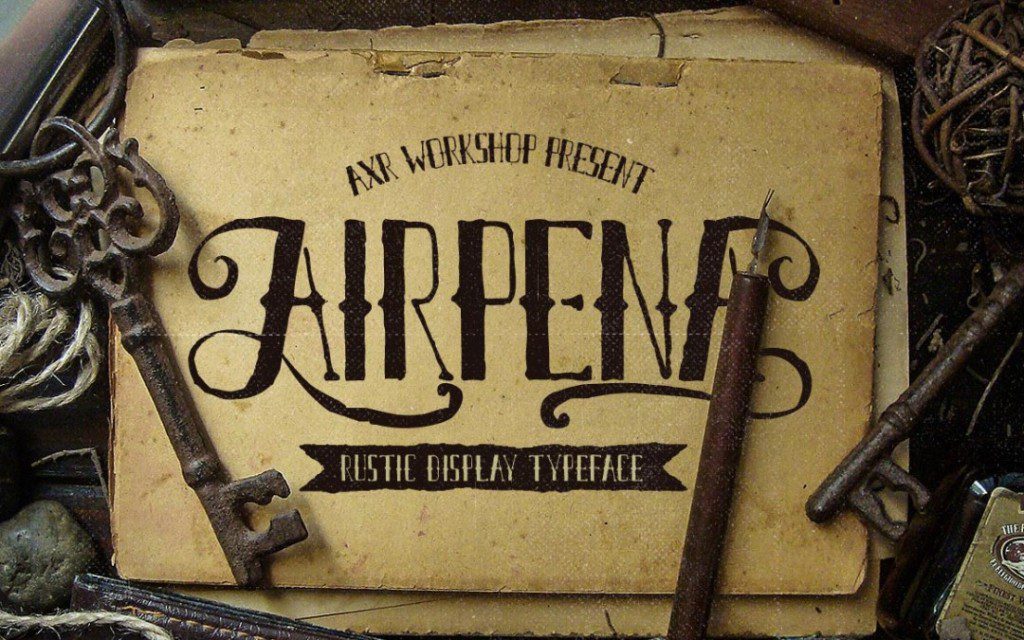
هذا محرف مجاني مستوحى من حروف مرسومة باليد صدئة ومؤلمة مستخدمة في دراجة نارية قديمة. يأتي مع بدائل أبجدية كاملة للأحرف الكبيرة (أمامي ونهاية) وأحرف صغيرة (نهاية).
2. Luxia - Modern Free Font
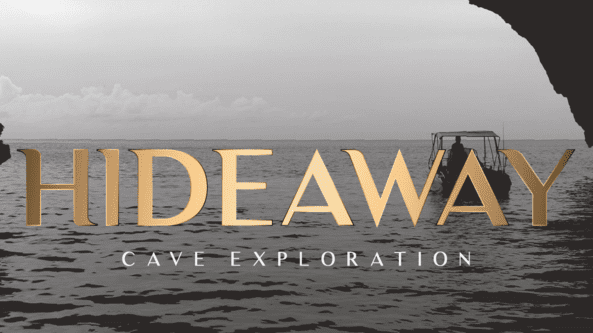
ألقِ نظرة على Luxia - ديدون حديث من سان سيريف مع مجموعة من الشخصيات الفخمة. يتضمن 3 أنماط: شبه غامق ، وشبه غامق مائل. لا تتردد! قم بتنزيل الخط المجاني وإنشاء عناوين جميلة باستخدام المحرف.
3. خروج - خط مجاني
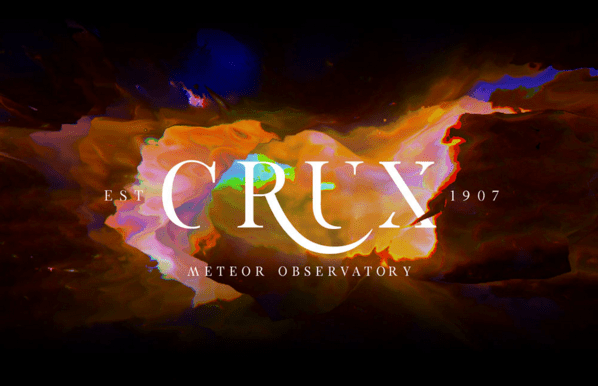
Exodus - خط مجاني بخطوط فاخرة. سيساعدك على إنشاء مجموعات أحرف فريدة من نوعها للشعارات والعناوين مع منح التحكم الكامل للمصمم. الهدية الترويجية من تصميم Andrew Herndon.
4. صوفيا - خط نصي للفرشاة Handlettered
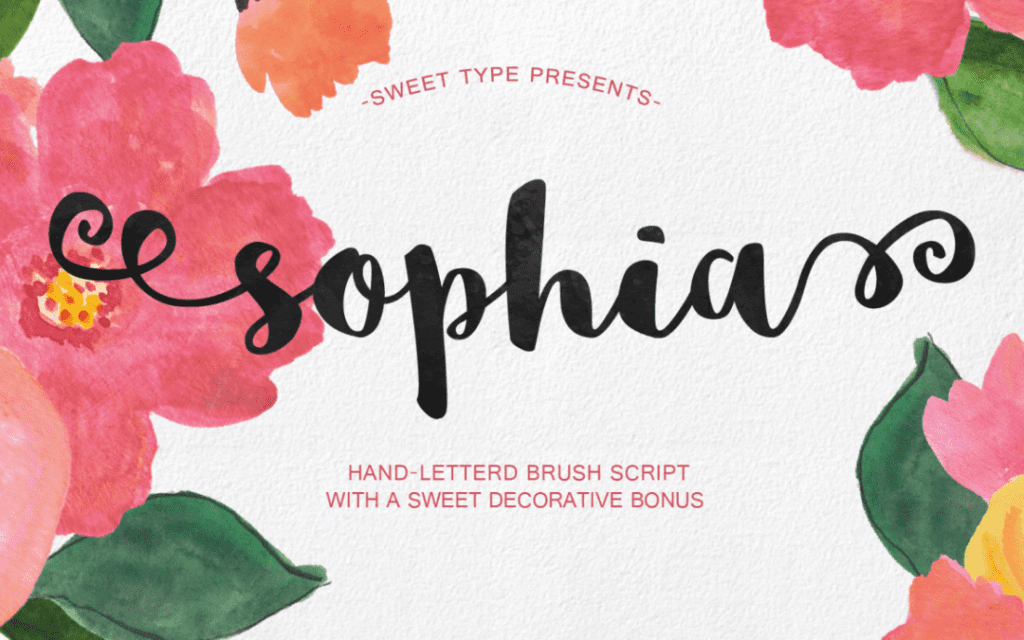
صوفيا - تنزيل جديد لخطوط فرشاة Handlettered Brush Script بواسطة إميلي سبادوني الموهوبة. في رأيي ، هذا الخط حلو للغاية ، بذيء وقليل من الرث. تسمح لك Sophia بإنشاء أنماط الكلمات المزخرفة الخاصة بك بسهولة. قم بالتنزيل مجانًا ببضع نقرات واستخدمها عبر مجموعة كبيرة من البرامج بما في ذلك Photoshop و InDesign و Illustrator و Microsoft Word بالإضافة إلى العديد من البرامج الأخرى.
5. Brusher الخط المجاني
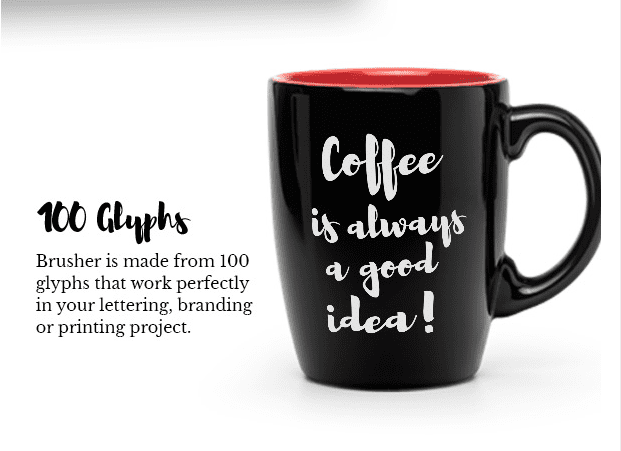
هذا خط تنزيل مجاني حديث وجريء للفرشاة يناسب تمامًا مشاريع التصميم المستقبلية الخاصة بك. يشتمل المورد على 100 صورة رمزية مصقولة بضربات دقيقة وخطوط ناعمة ستمنح النص مظهرًا يدويًا بشكل طبيعي.
6. Wask جديد - مكثف ، خط Sans Serif مجاني
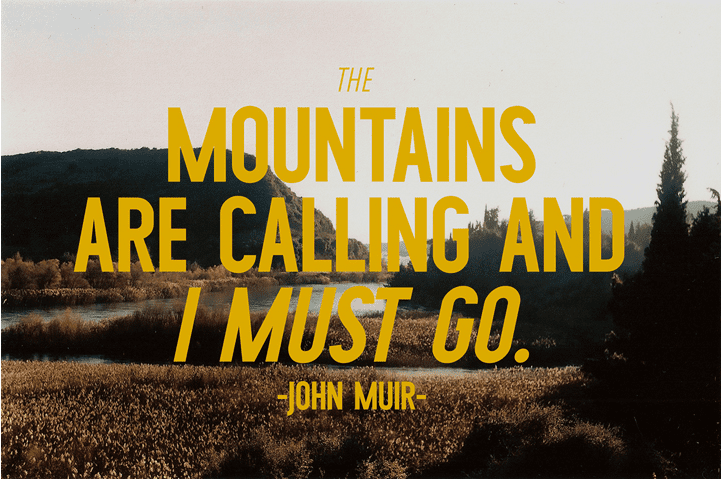
الهدية الترويجية من تصميم فاسيليس سكاندالوس. يتضمن الخط المجاني وزنين وحتى نمط مائل. إنها مناسبة للأغراض التجارية والإعلان والتعبئة وأيضًا للمطبوعات.
7. Parabola خط اليد الحرة الخط
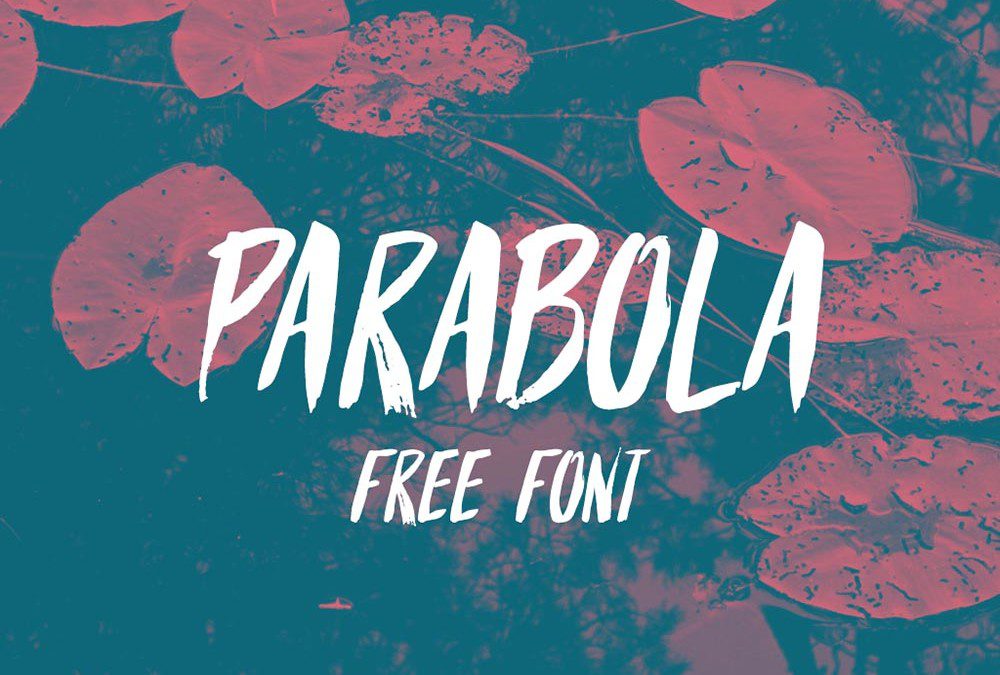
Parabola هو خط مجاني رائع مكتوب بخط اليد للملصقات والعناوين. هذا الخط هو نمط فرشاة رائع حقًا وهو متوفر بالتنسيقات: OTF TTF ومجموعة خطوط الويب. يبدو رائعًا لأي نوع من المشاريع ، خاصة مشروع التصميم الذي يحتاج إلى خط مكتوب بخط اليد بلمسة شخصية.
8. اليراع: خط مجاني مرسومة بخط اليد
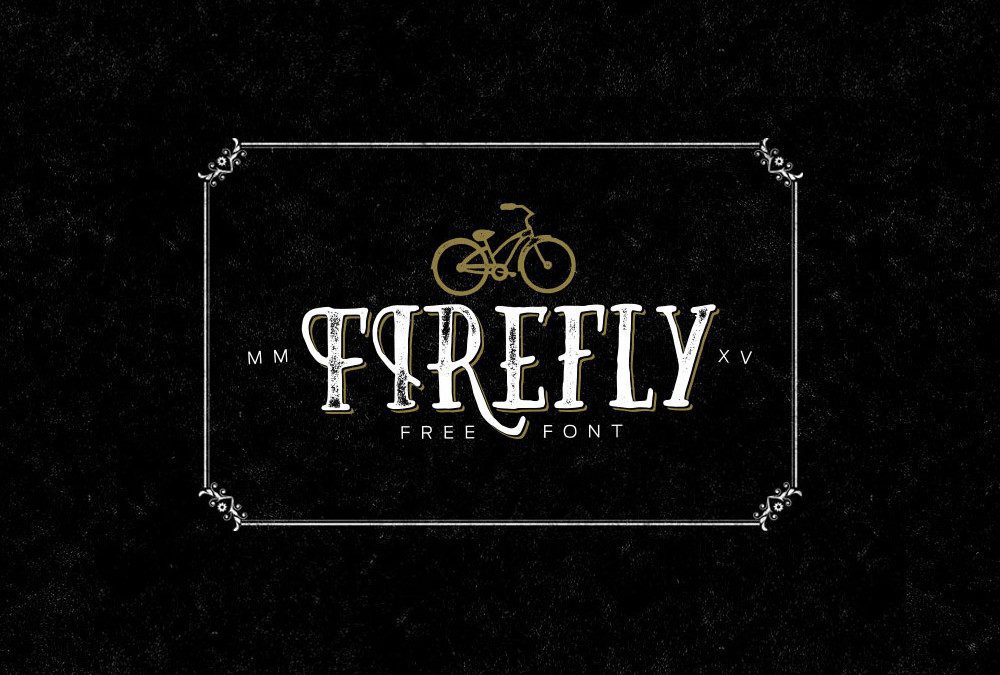
Firefly: Hand Drawn Free Font تنزيل . إنه رقيق ملتوي مع الكثير من الشخصية والسحر ويأتي مع مجموعة كاملة من الحروف الرسومية وبعض البدائل. يعمل الخط المجاني بشكل رائع مع عروض الأسعار والشعارات والملصقات والعناوين الرئيسية والقمصان وغيرها الكثير!
9. الخط المجاني - سوريا
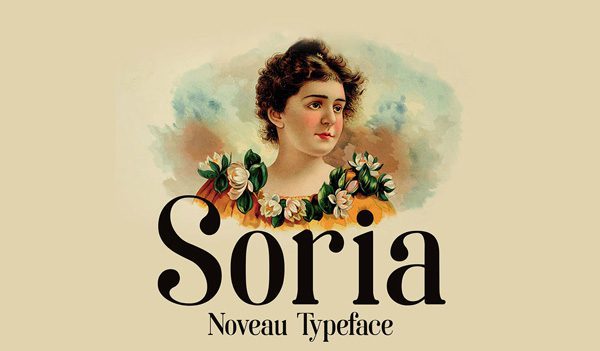
تم إنشاؤه تحت التأثير الحديث. استخدم هذا الخط لمنح مشاريع تصميم الويب أو مشاريع التصميم الجرافيكي مظهرًا أنيقًا.
10. خط مجاني - Elrotex
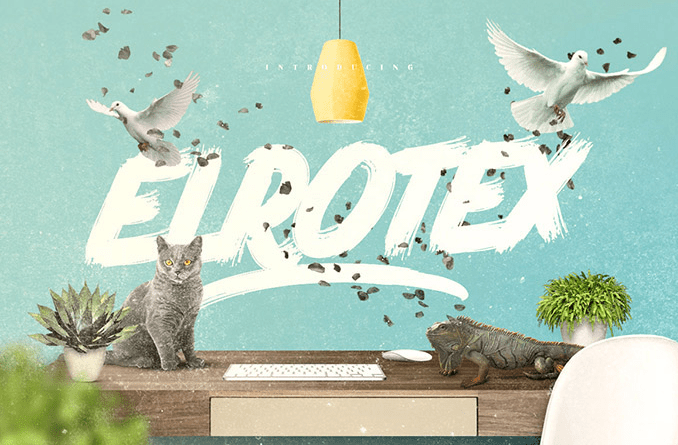
سيعطي محرف الفرشاة الرائع والفريد من نوعه تصميمك مظهرًا يدويًا مذهلاً. يتوافق مع أي مشروع إبداعي ، مثل عروض الأسعار والشعارات والتعبئة والقمصان.
11. الخط المجاني - Humblle Rought
هذا محرف حديث عتيق بتدفق غير مثالي يمنح النص مظهرًا طبيعيًا. يتضمن هذا الخط المذهل أيضًا أحرفًا ورموزًا خاصة ومجموعة مختارة من البدائل الأسلوبية. يمكن أن تتفق مع الشعارات والتغليف والقمصان وأكثر من ذلك.
12. فينتيج فونت مجاني - Moabhoers
في هذه المرة ، يسعدنا جدًا أن نشارك معك خطًا عتيقًا مجانيًا ومميزًا ومخصصًا رائعًا - Moabhoers من Agga Swist'blnk. خط كامل / محرف بأسلوب عتيق رائع. بالإضافة إلى ذلك ، احتوت أيضًا على أحرف خاصة.
13. سيناريو قائمة التشغيل - خط مجاني
هذا تصميم خط مجاني مخصص للبرنامج النصي - نص قائمة التشغيل. هذا خط نصي رائع مرسوم يدويًا بنمط الفرشاة. تحقق من الموقع ولا تتردد في تنزيله واستخدامه لمشروعك التالي. يتمتع!
14. يهوذا - الخط الحديث المجاني
يعتمد هذا الخط المجاني على شعار فرقة British Heavy Metal الشهيرة. إنه قابل للتخصيص ويمكنك استخدامه لأي شيء تريده.
15. محرف مجاني - نص جلاديستا
إنه محرف خط حديث مع خط أساسي للرقص. يجمع هذا الخط بين حروف الفرشاة والكتابة اليدوية التقليدية. ينسجم مع العلامات التجارية الشخصية وبطاقات العمل وملصقات الاقتباس والمزيد.
16. ايدان - سيناريو رومانسي
Aidan هو chirography الحديثة مع حركة رومانسية وملفتة للنظر. يتوافق مع دعوة زفاف ، تصميم بألوان مائية. يناسب أيضًا أي شيء يحتاج إلى شعور طبيعي. يمكن استخدام الخط للأغراض الشخصية والتجارية.
17. الحياء - الخط
اجعل مشروعك الجديد مثيرًا للإعجاب مع Free Font - Modesty الجديد. هذا خط خطي بحركة رومانسية ورائعة. يتوافق مع العلامة التجارية وتصميم المدونة والتصميم الإعلاني الحديث وكتاب الصور والمزيد. لا تتردد في استخدامه للأغراض الشخصية والتجارية.
18. شيء وايلد - خط مجاني
هذا محرف مكتوب بخط اليد بروح جامحة أصيلة ستجعل تصميمك فريدًا ومميزًا في الحشد ، وبالتأكيد سيكون له تأثير عميق على مشاهديك. يأتي Something Wild بجميع التنسيقات الشائعة. فقط الشيء الصحيح بالنسبة لك إذا كنت ترغب في إضافة بعض الشعور الخام في التصميم الخاص بك!
19. سليمة - مودرن فونت
هذا خط مجاني حديث - سليمة. يتضمن 194 حرفًا رمزيًا (أساسي وممتد لاتيني وعلامات ترقيم وأحرف خاصة والمزيد). يأتي الخط المجاني بمظهر فرشاة طبيعي وعفوي.
20. King City - خط فريد من نوعه للخط الحر
King City - خط فريد من نوعه للخط الحر ومثالي للتصميم ، وتصميم العناصر ، والزفاف ، والملصقات ، والعمل الرائع ، والحدث ، والقميص ، والشعار ، والشارات ، وما إلى ذلك ... الخط عبارة عن مزيج من خطوط الربط البديلة ويسهل تخصيصه.
21. جاستن رود - مجموعة خطوط الفرشاة المجانية
هذا الخط مناسب للعلامات التجارية ، وتصميم القرطاسية ، وكتاب الصور الحديث ، والمخطط ، وتصميم حياة المشروع أو الكمبيوتر الدفتري ، وتصميم المدونات ، والزفاف ، والمناسبات الخاصة ، وأي احتياجات من الحروف ، وتصميم الإعلانات الحديثة ، والدعوة ، والمزيد.